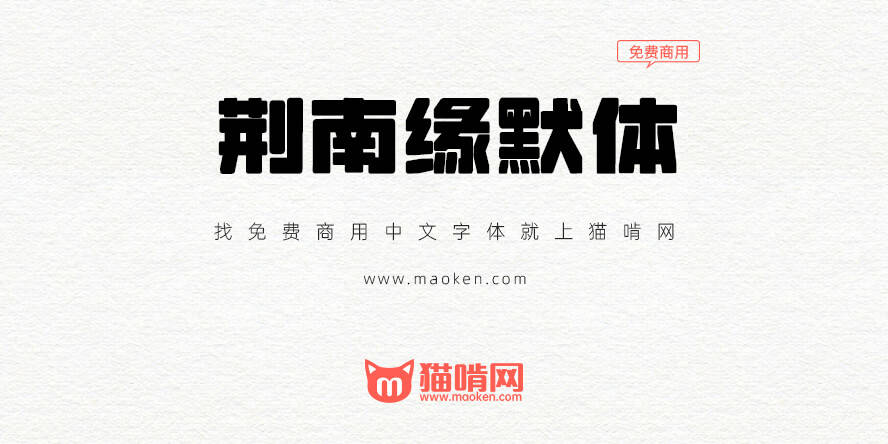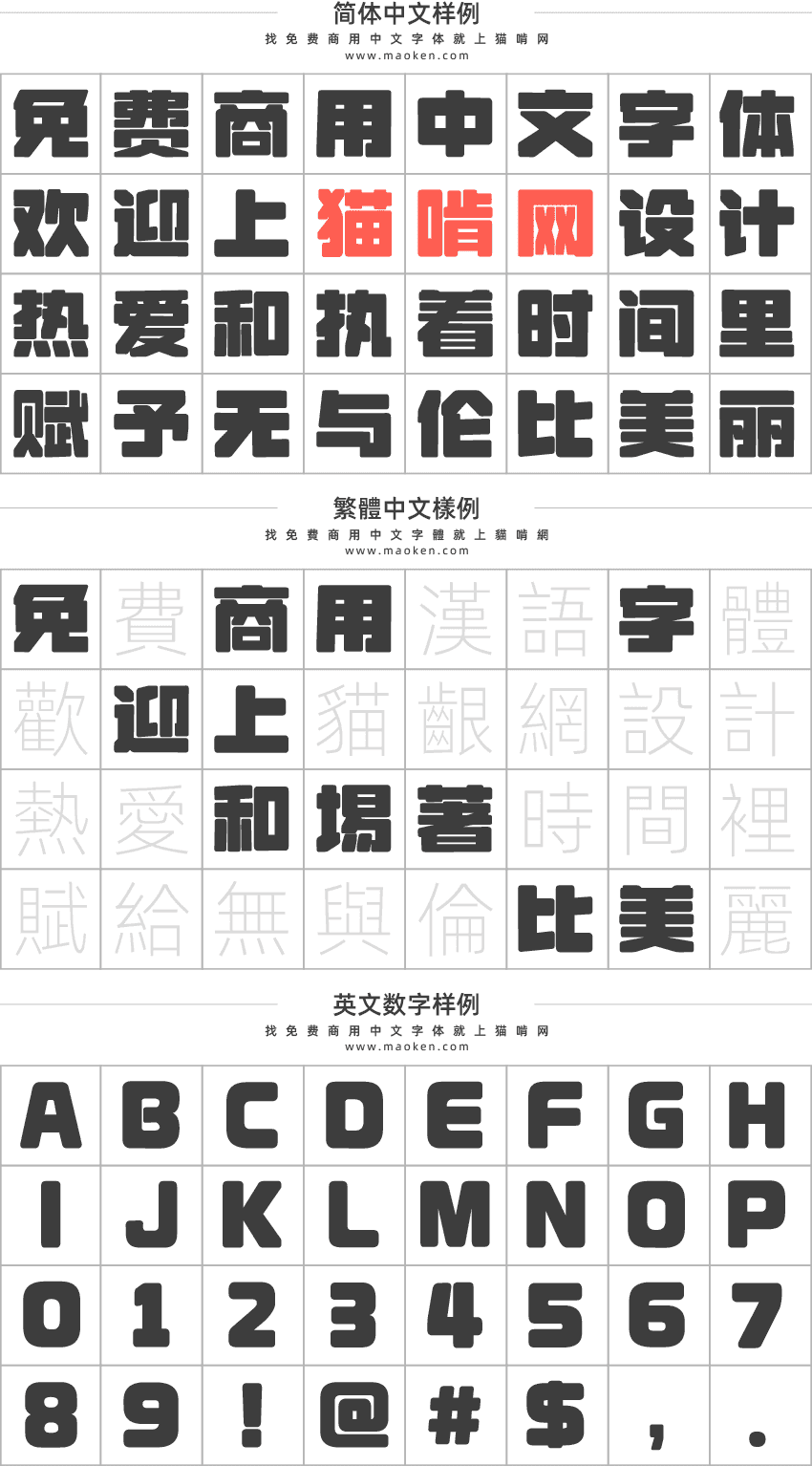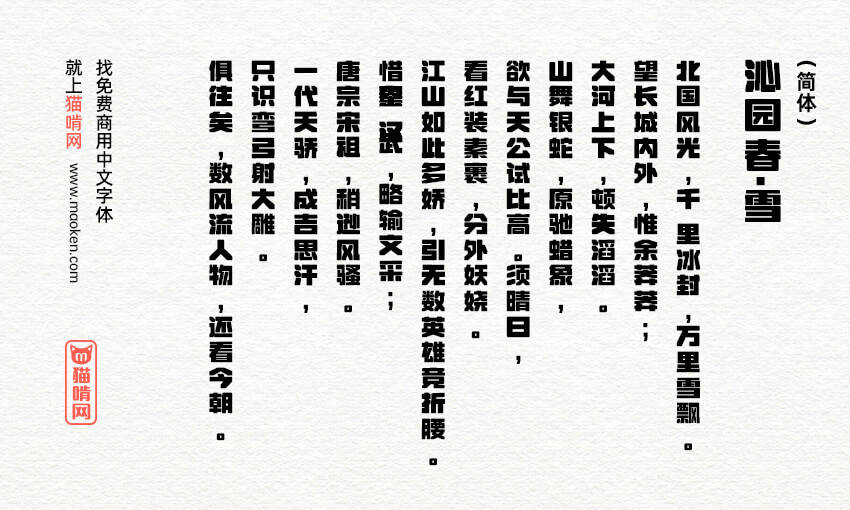
荆南缘默体:专为标题设计而生的粗黑广告宣传类字体
字体作者:荆南字坊 (中国大陆) 字体字重:1个
2020年突如其来的疫情,让我想创作一套属于自己的字体的愿望从遥不可及的理想变成了触手可及的现实。总想着这套字体一定要是在大街上随处可以见到的那种风格。什么样的字体最受欢迎?经过我个人的仔细观察,发现还是粗的类综艺黑体的美术字最受欢迎,这类字体总能在第一时间抓住人的眼球。于是我就按照自己的想法绘制了一种尽可能占满一个偏扁的长方形的粗黑字,没想到从去年年初到现在一年多的时间居然还把将近7000字的完整版做完了。
一开始的字体风格还不想现在这样,圆角是后来逐渐加上去的,我想要一种增加字体趣味性但是又不要看起来很像叠圆体之类的圆体美术体,于是就形成了如今的圆角。
理想的设计用途:该字体非常适合店招、房地产广告、地铁公交站广告海报、线上及线下的各类产品宣传、个人VLOG封面标题字体等。
字体特点
在尽可能保持字形辨识度的情况下,笔画尽可能的粗,字尽可能占满一个方格
笔画过多的字某些笔画做特殊粗细对比处理
字框偏扁,重心偏低
包含了西文、数字、符号、日文平假名、日文片假名、注音符号、汉语拼音等
Ver 0.74(2024/05/15)
• 修正“举”“串”
• 修改部分字体的偏旁
Ver 0.73(2024/04/18)
• 更改了翀翂翋翦诳邸燕漶患器啼这些字
• 字体的版本号没有更改
Ver 0.73(2023/04/30)
• 修复部分字笔画未合并的BUG
• 修改假名设计
Ver 0.71(2022/08/13)
• 修复:姊、姑码位错误的问题
Ver 0.7(2022/07/27)
• 修改部分字的写法布局
Ver 0.6(2022/05/22)
• 修改了部分字的内白
• 增加部分汉字
Ver 0.5(2022/02/19)
• 补全《通用规范汉字表》表内字
• 调整部分字形
• 新增「頫」字
Ver 0.17(2021/11/20)
• 修复了「缟」「缠」两个错字
Ver 0.16(2021/09/12)
• 荆南缘默体更新0.16版本,优化竖版排版。
Ver 0.15(2021/08/30)
• 荆南缘默体更新0.15版本,优化部分字型
Ver 0.14(2021/08/09)
• 荆南缘默体更新0.14版本,优化部分字型
Ver 0.13(2021/04/24)
• 荆南缘默体更新0.13版本,优化字体的笔画粗细及灰度
Ver 0.12(2021/02/04)
• 修改了大部分幺作为部首的写法
• 增加了嘸嚟喺冧冚哋怹瞓餸噁(方言和特殊用途用字)
• 修复了せぜ这两个假名显示错误的问题
• 优化了部分偏旁
Ver 0.11(2021/02/03)
• 修复了错误显示的字“埸、侑”
• 调整了部分假名的写法
• 调整了大写字母和字母间距
• 更改了「饣」部首的写法和滋字的写法
• 调整了部分小字号会糊的字
Ver 0.10(2021/02/01)
• 荆南缘默体测试版正式发布